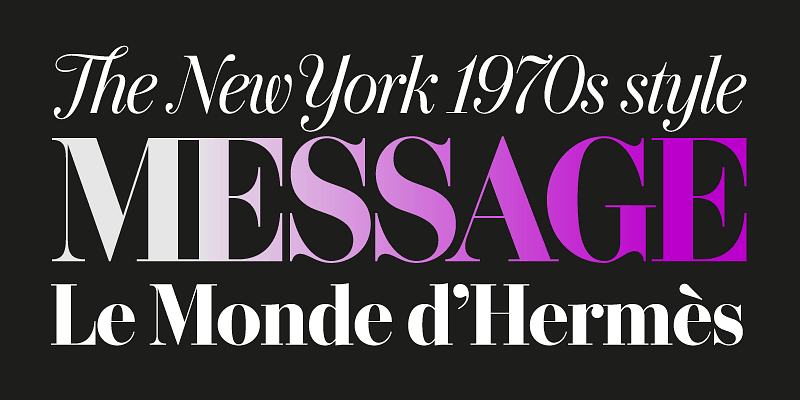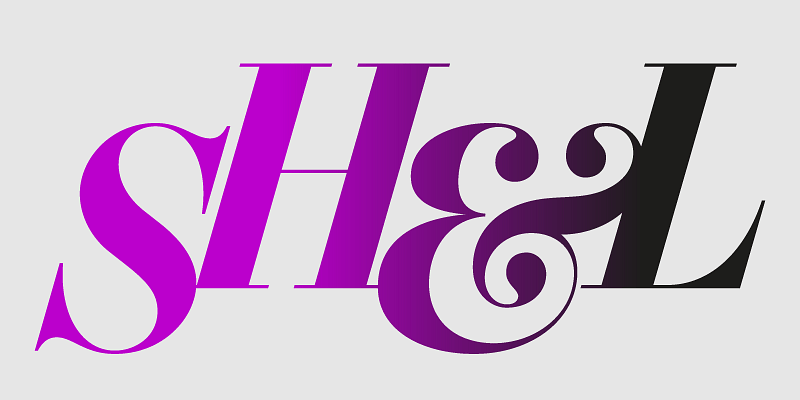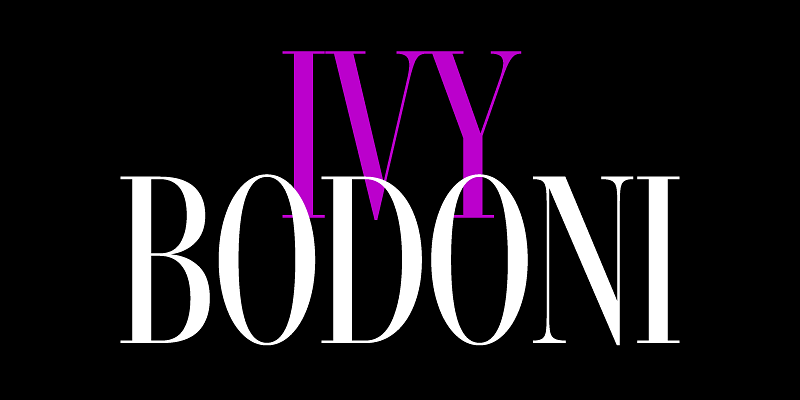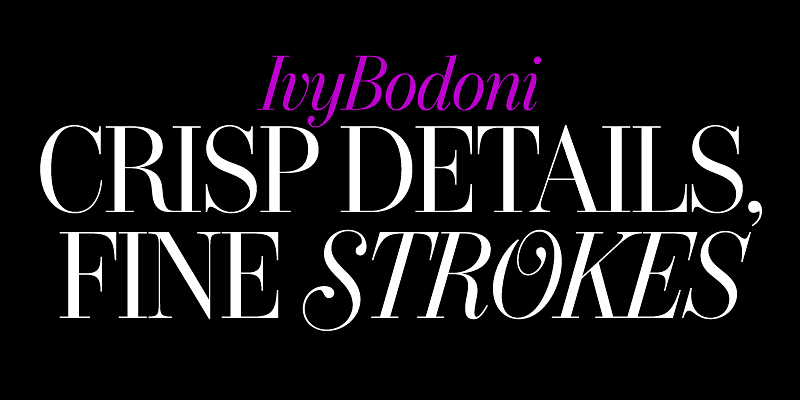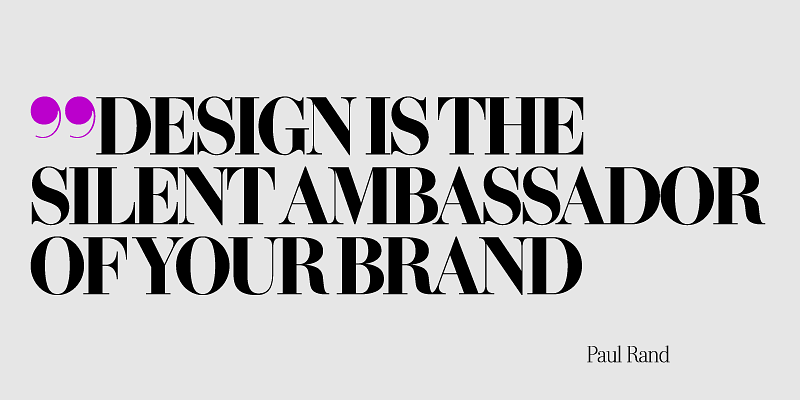
IvyBodoni rinde homenaje a los diseños con serifa modernos de los años 60 y 70. Tipos de letra como Pistilli Roman, Didi y CBS Didot, y artistas de la rotulación como Mortimer Leach y Tommy Thompson, inspiraron las decisiones de Jan Maack al dibujar las líneas nítidas, los terminales de bola distintivos y las curvas precisas. Esta Bodoni del siglo XXI se diseñó para usos de moda y editoriales, y es ideal para cualquier necesidad tipográfica de cartelería. IvyBodoni está disponible en 6 grosores, 2 anchuras, cursiva y 2 fuentes variables.